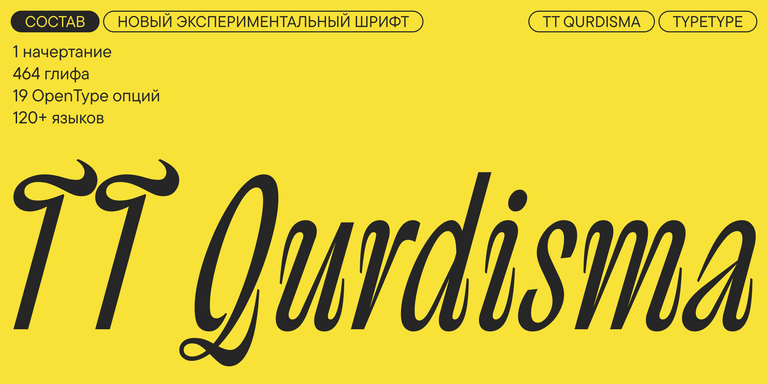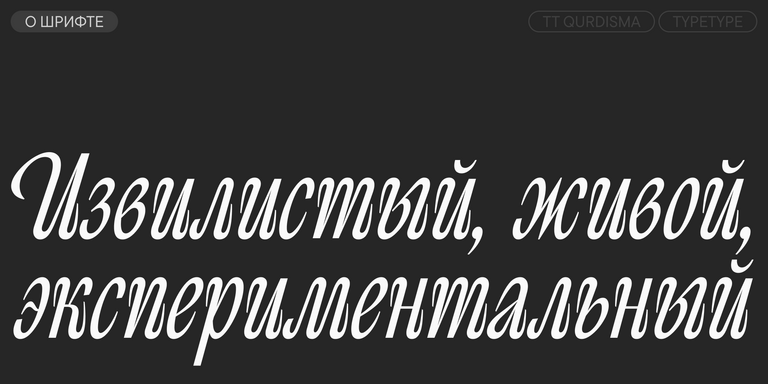
Шрифты для айдентики
TT Odellia — старостильная антиква с современным рисунком, вдохновлённая венецианскими шрифтами и классической музыкой.
TT Nooks Script — шрифт с уникальным рисунком, который не имеет прямых аналогов.
TT Qurdisma — узкий и плотный декоративный шрифт, напоминающий причудливое растение. Вьющиеся, плавные контуры рождают растительный орнамент.
TT Rationalist — функциональный и оригинальный брусковый шрифт с актуальным рисунком. Он универсален и подходит как для заголовков, так и для массивов текста.
TT Runs — это выразительный шрифт, который идеально впишется в проекты со спортивной тематикой. При этом гарнитура отлично подойдет и для других современных проектов: после обновления сфера ее применения значительно расширилась.
TT Turns — геометрический гротеск с акцентными круглыми знаками и выразительными нависающими элементами. Это универсальный шрифт, который лаконично выглядит и отлично читается в маленьком размере, при этом в крупных кеглях становится акцидентным и проявляет свой характер на максимум. Он энергичный, сильный и динамичный — особенно отчётливо это проявляется в наклонных начертаниях.
TT Quaris — изысканная и современная ленточная антиква. Перед разработкой этой гарнитуры мы провели глубокое исследование архетипов ленточных антикв.
TT Bakers — пластичная антиква с нежным и живым характером. Этот шрифт похож на свежую выпечку: он тёплый и мягкий, особенно в жирных начертаниях.
TT Modernoir — акцидентный гротеск с разноширинными пропорциями. Плавные линии и изящные формы ар-нуво в этом шрифте сочетаются с ритмичностью и импровизационной свободой джаза.
TT Marks — рукописный шрифт с динамичным ритмом, тёплым характером и слегка ностальгическим настроением. Он вдохновлён классическими американскими расписанными вывесками (sign painting), которые когда-то художники создавали вручную с помощью кистей и красок. Сегодня надписи в таком стиле снова набирают популярность.
TT Fellows — гуманистический гротеск с механистическими мотивами. Открытые формы, дружелюбно-нейтральный характер тонких весов и ещё более мягкий характер в жирных начертаниях.
TT Disruptors — дуктальный рукописный шрифт, созданный с помощью маркера. Его рисунок уникален: потёртости, неравномерная толщина штрихов и удлинённые выносные элементы придают ему живую, динамичную текстуру и ощущение рукотворности. Характер этого шрифта своенравный и эмоциональный, но при этом тёплый и душевный.
TT Gentlemens — динамичный рукописный шрифт, в котором серьёзность и чёткость письма сочетается с элегантностью и изысканностью. У него характер и стиль настоящего джентльмена: сдержанный и всегда уместный, но при этом уверенный и эффектный.
TT Gertika — геометрический гротеск с динамичным характером и танцующим ритмом. Идея шрифта зародилась из леттеринга на американском плакате второй половины 30-х годов.
TT Biersal — акцидентный гротеск со свободным, озорным и авантюрным характером. Отправной точкой для его создания послужил немецкий плакат начала 30-х годов. Мы хотели сохранить не только пропорции, но и ощущение небрежности, живости леттеринга из референса.
TT Cometus — современная брусковая антиква. Название гарнитуры отсылает к образу кометы — мощного увесистого тела с красивым хвостом, грациозно рассекающего космические просторы с огромной скоростью.
TT Ricks — выразительная антиква с острым характером. Создавая ее, мы вдохновлялись шрифтом De Vinne, разработанным Густавом Шредером в 1892 году. Это «злая» антиква, которая, впрочем, иногда усмиряет свой дерзкий нрав.
TT Espina — дисплейная антиква с выразительными засечками. При ее создании дизайнеры вдохновлялись исторической формой буквы «O», которая приобретала ромбовидную форму из-за качества печати. В каждую букву хочется всматриваться, так что заголовки, оформленные TT Espina, точно привлекут внимание.